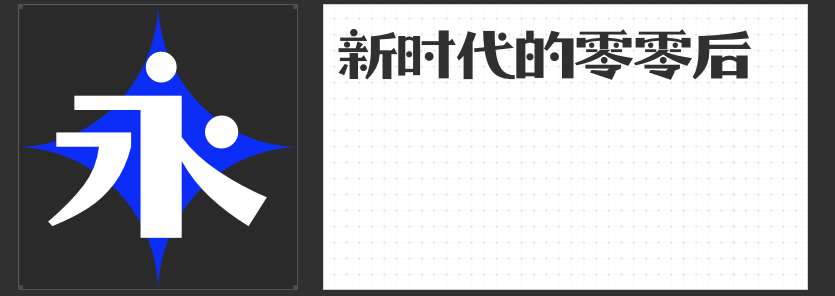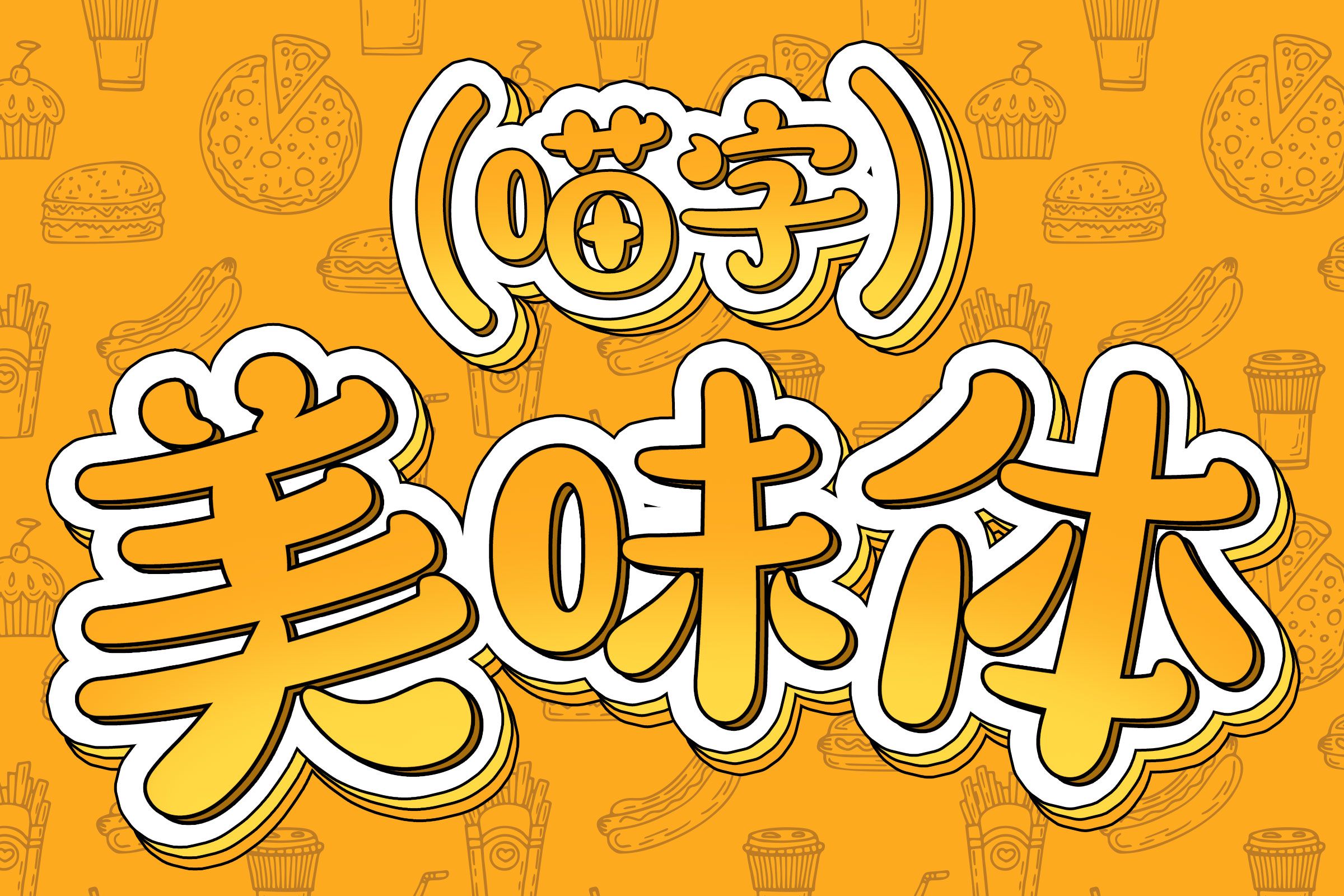
四款可❤️爱❤️风字体推荐,为设计注入灵动活力
在设计的世界里,可爱风格的字体宛如灵动的精灵,能为作品增添别样的魅力与温度。今天就为大家推荐四款风格可爱的字体,让你的设计瞬间“萌”力四射。
一、励字小星星简
励字小星星简俏皮可爱,满是童稚趣味,是具有现代审美装饰趣味的书写字体。它精心设计每一笔一划,拙朴的线条却有着极高的辨识度,布白均匀,风格独特且节奏鲜明。在二次元及三次元的视觉语境中,它都能将儿童的童稚可爱展现得淋漓尽致。无论是制作儿童玩具包装、卡通动画海报,还是充满童趣的网页设计,励字小星星简都能唤醒人们内心深处对童年的美好向往。
二、字恋狂零零后简繁
字恋狂零零后简繁字体中融入圆形小球元素,无规则地散落在每个字当中,调皮又可爱。部分笔画设计成拱形的弧线,曲直结合,相映成趣。这种独特的设计风格,让它非常适合用于面向年轻群体的设计,如潮流服饰宣传海报、青春主题的社交媒体内容等。它能为设计增添一份灵动与活泼,让年轻受众产生强烈的共鸣。
三、喵字美味体
喵字美味体是专为餐饮行业打造的特色字体。它以圆润、饱满为核心要素,笔画转折间流露出满满的温暖与丰盈感,营造出视觉上的舒适享受。在餐饮菜单、餐厅海报、外卖包装等设计中使用喵字美味体,能让人仿佛感受到食物的鲜美和环境的温馨,增强消费者的食欲和消费欲望。
四、喵字文案体
喵字文案体专为文案行业量身打造,巧妙融合传统书法的韵律与现代设计的简洁,每一笔一划都透露着知性之美。它强调阅读的流畅性和视觉的舒适度,无论是广告创意、品牌故事叙述,还是社交媒体内容的编排,都能精准捕捉文案的精髓,赋予文字以温度和力量,让文案更加生动、富有感染力。
这四款可爱风格的字体各具特色,能为不同类型的设计增添独特的魅力,让你的作品在众多设计中脱颖而出。